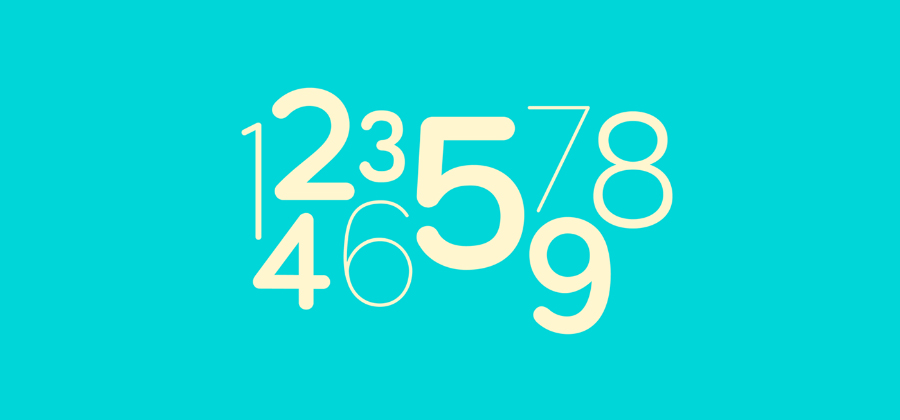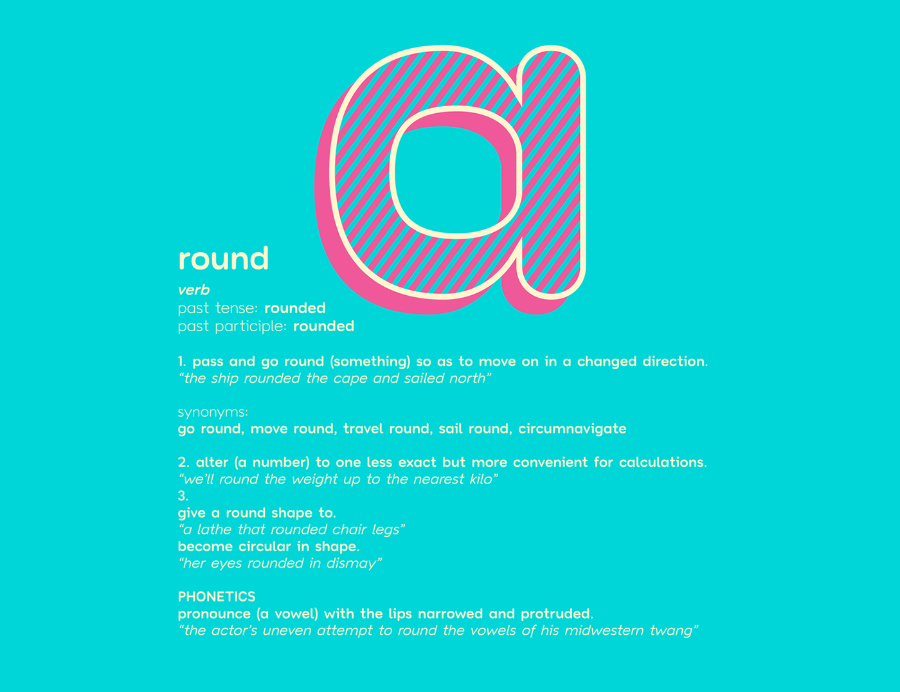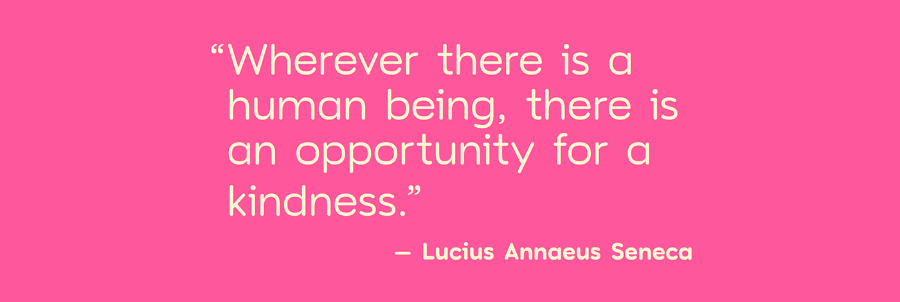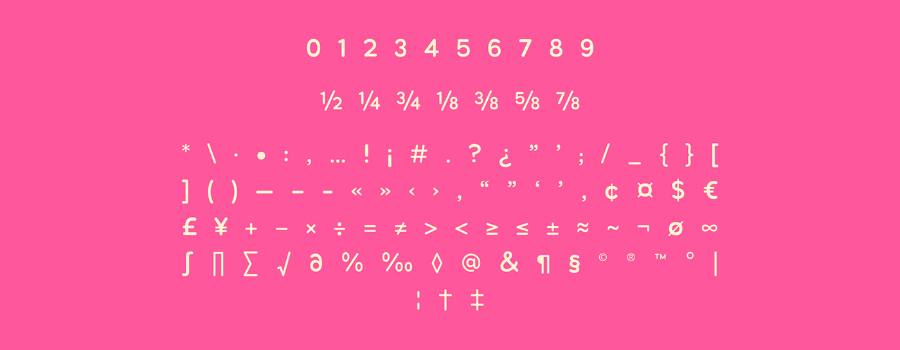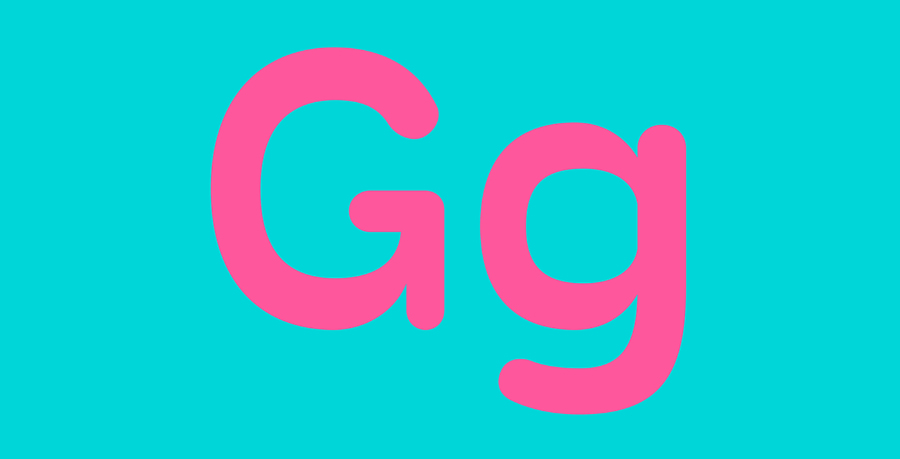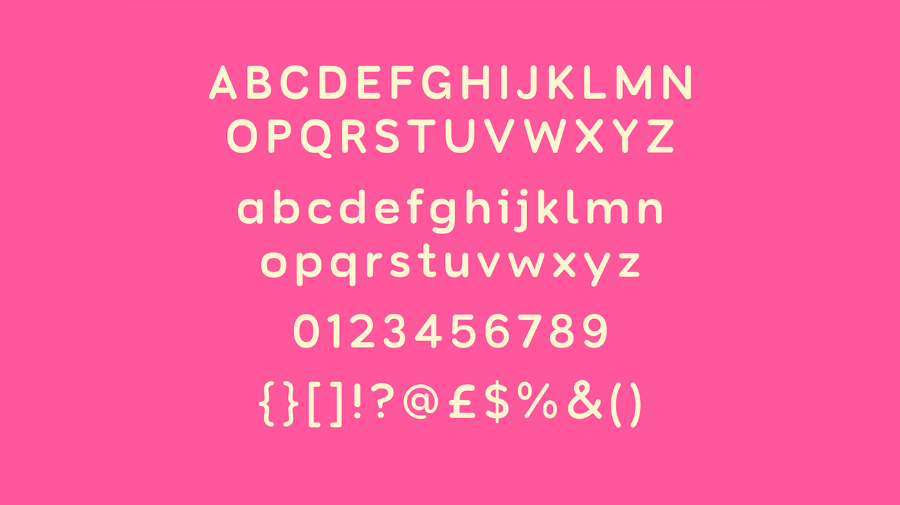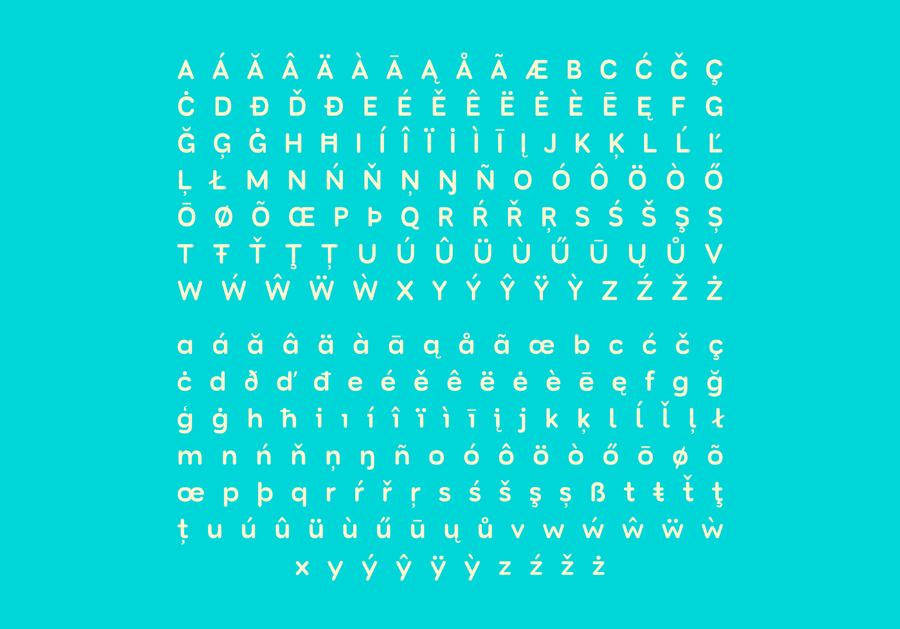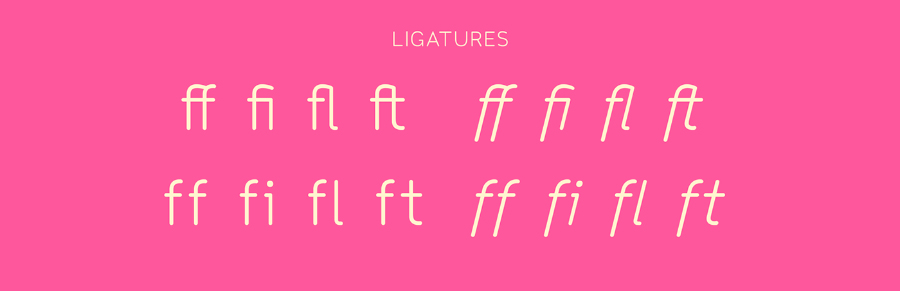
今天,你可以有Toriga字体免费演示。这个字体的名字是来自葡萄牙葡萄品种Touriga Nacional。这个有趣的字体拥有一个平衡,多功能,现代的无文字字体高清晰的功能。但它也具有一个干净,优雅的外观作为一个更大的显示字体。此外,圆形终端给人以友好,平易近人的感觉。这是伟大的品牌,正文,标题等等!